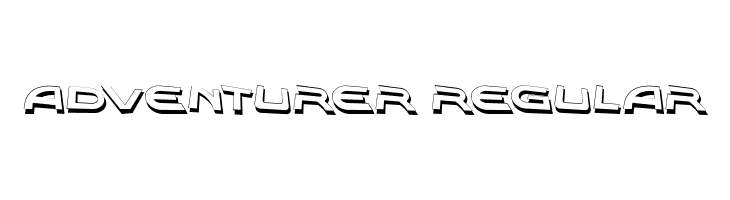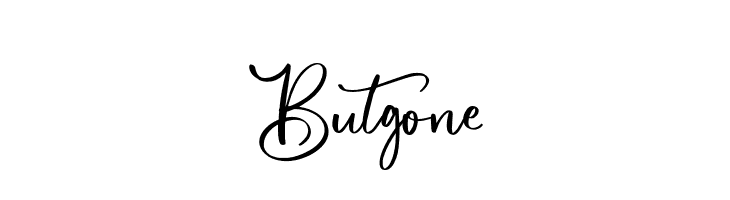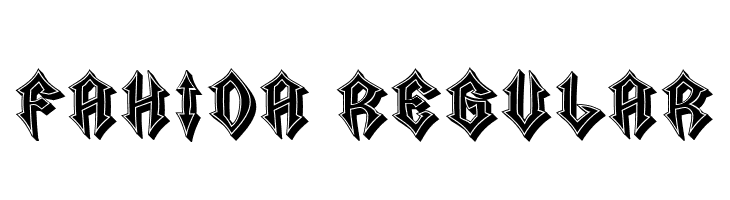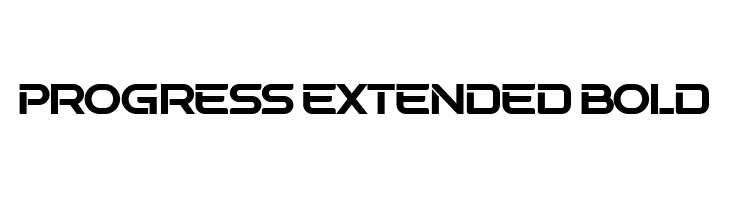
( OVERWATCH )
A bold, futuristic font with sharp angles and geometric shapes.
( Fonts by Barland )
An elegant script font with flowing, ornate characters and graceful numerals.
( tricky )
An eclectic and artistic font with unique, whimsical character designs.
( Fonts by David Tessier )
An elegant and ornate script font with flowing, high-contrast strokes.
( Fonts by Hanoded )
A rugged, hand-drawn font with a distressed, vintage appearance.
( Fonts by Siwox Core LineType )
An elegant and flowing script font with graceful curves and loops.
( READY PLAYER FONTE )
A bold, geometric font with a futuristic and playful design, featuring unique cutouts and patterns.
( Fonts by dcoxy )
A dynamic and flowing script font with elegant, slanted letterforms.
( Fonts by Adam Fathony )
An elegant script font with flowing, ornate letterforms and intricate loops.
( Fonts by xpeehdroox )
A dynamic and fluid handwritten script with elegant, sweeping curves.
( austiebost.net )
A playful, hand-drawn font with a whimsical and artistic style.
A sleek, geometric font with consistent stroke width and modern design.
A modern, geometric font with bold lines and sharp angles.
( Fonts by Intellecta Design )
An elegant script font with flowing, cursive letterforms and dynamic stroke variations.
( Fonts by Ferry Hadriyan )
A dynamic and elegant script font with flowing, cursive design.
( Fonts by Ferry Hadriyan )
A dynamic and flowing script font with elegant cursive letterforms.
( Fonts by itypeface )
An elegant script font with flowing, cursive letterforms and a sophisticated appearance.
现在大家都在用哪些新字体?
流行变化很快,但极简无衬线与个性鲜明的展示体当前更受欢迎, 特别适合移动端内容与现代品牌风格。
有哪些值得尝试的 5 款新字体?
近期热门包括 OVERWATCH, YulindaScriptDemo, funQuandary, Roller Coaster and Jeannette 它们在清晰度与个性之间取得平衡,适用于科技品牌、编辑排版与社媒视觉。